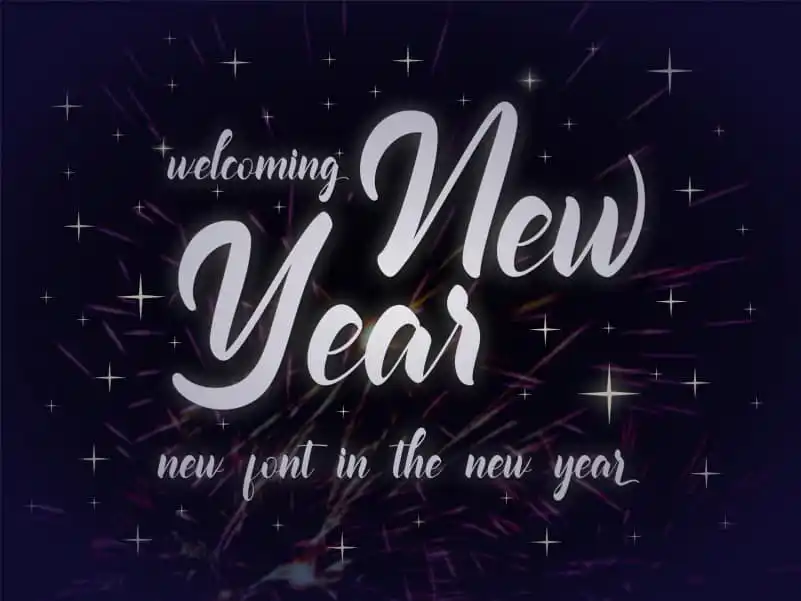
Welcoming New Year Script Font – Download Grátis
A ‘Welcoming New Year Script Font’ é uma maravilhosa seleção para qualquer designer ou artista que deseja um estilo elegante e envolvente para seu trabalho durante o ano novo. Esse script font foi meticulosamente projetado, fornecendo uma aparência quase autêntica de letra escrita à mão. Suas linhas leves, suas formas delicadas e sua tipografia fluida criam um ambiente acolhedor que pode transformar simples ideias em criações incríveis. Nuryanto Dwi é o designer responsável por este extraordinário design de fonte, dedicando tempo e cuidado para criar algo singular. A ‘Welcoming New Year Script Font’ tem a capacidade de elevá-lo ao próximo nível de criatividade. E com seu estilo elegante e moderno, pode ser usado em uma ampla variedade de trabalhos desde cartões festivos até design gráfico e criação de identidades corporativas. Ao adquirir essa fonte, você se tornará um convidado especial na festa de criatividade. Cada caractere é um convite para explorar novas possibilidades, fazendo seu trabalho ainda mais único e poderoso. Não perca essa oportunidade única de adicionar uma personalidade única a seus projetos digitais.